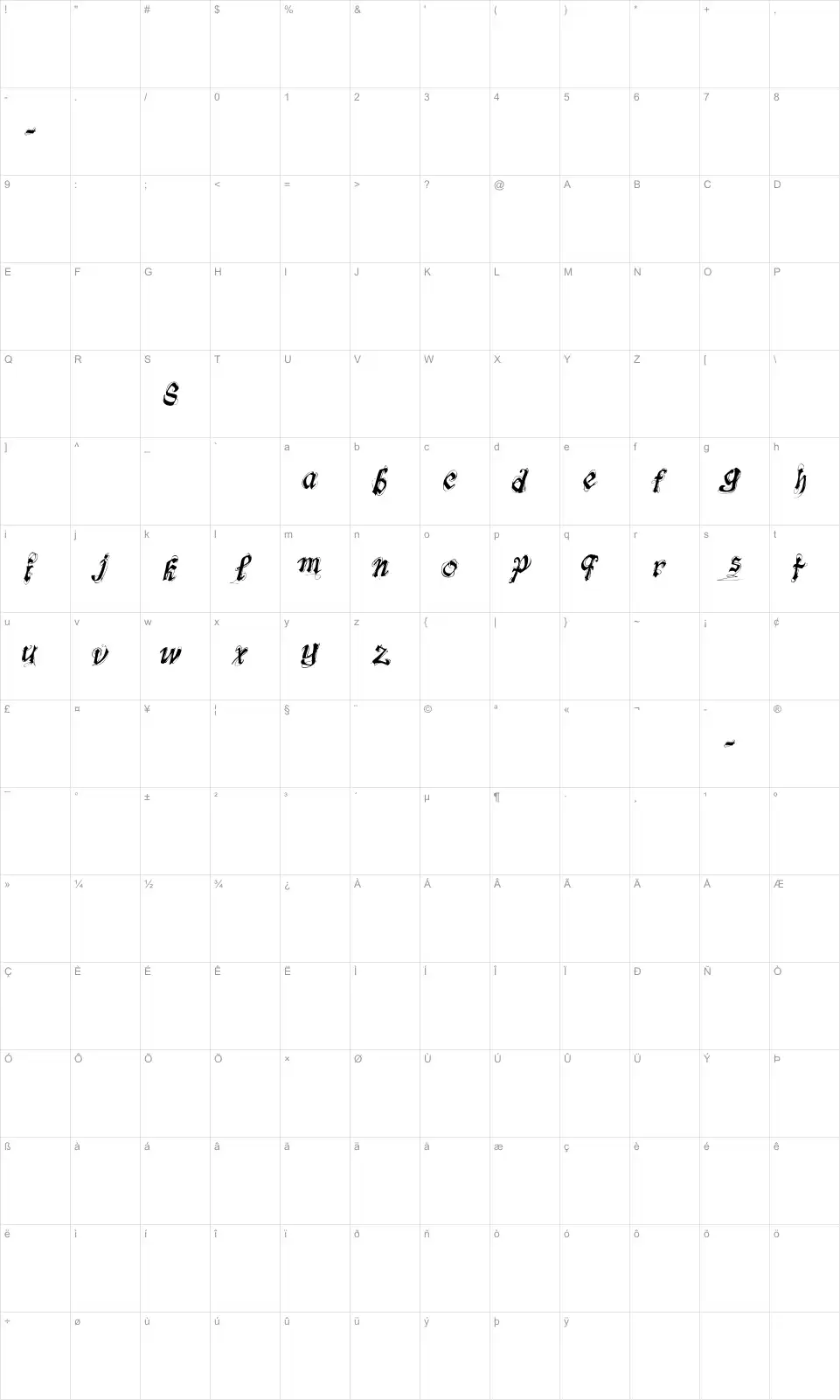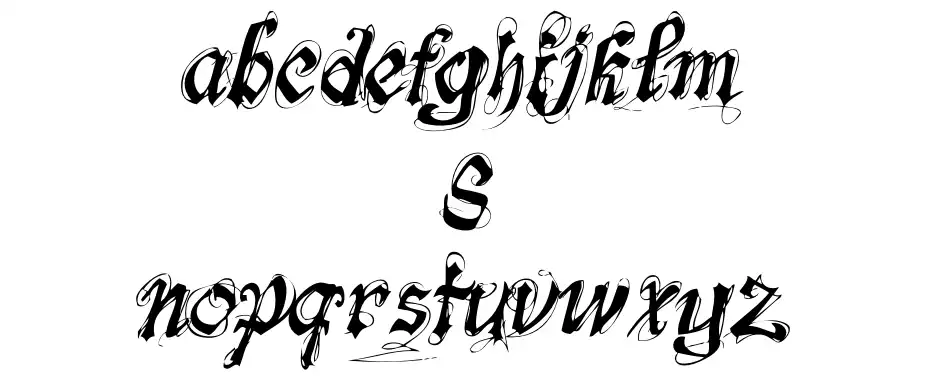
Fonts-Lab Symphony
A Fonts-Lab Symphony é uma fonte criada por Fontscafe.com que combina elegância e elegância, perfeitamente adequada para o tema festivo do Dia das Crianças. Se você está procurando por esta fonte específica, agora pode baixá-la ou gerar um preview personalizado para seu texto online para ver como ela se destaca antes de usá-la. A fonte pertence à categoria Holiday, especificamente a festa de Natal. Adicionada em 12 de julho de 2022, já foram baixados 5434 cópias desta fonte, cada uma representando um pequeno presente de Natal digital. Com um tamanho de 372 KB, a Fonts-Lab Symphony é compacta e pronta para uso, e você pode encontrá-la no site do criador, Fontscafe.com.
Designer: Fontscafe.com